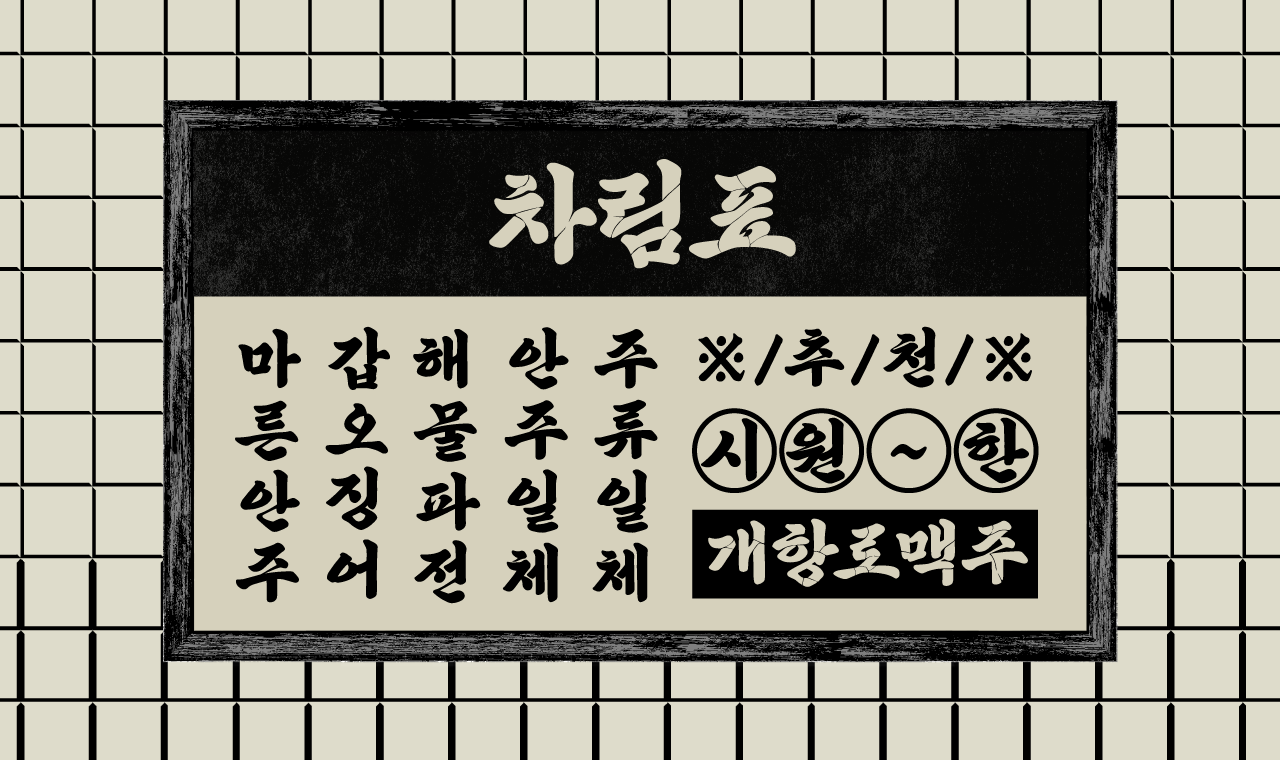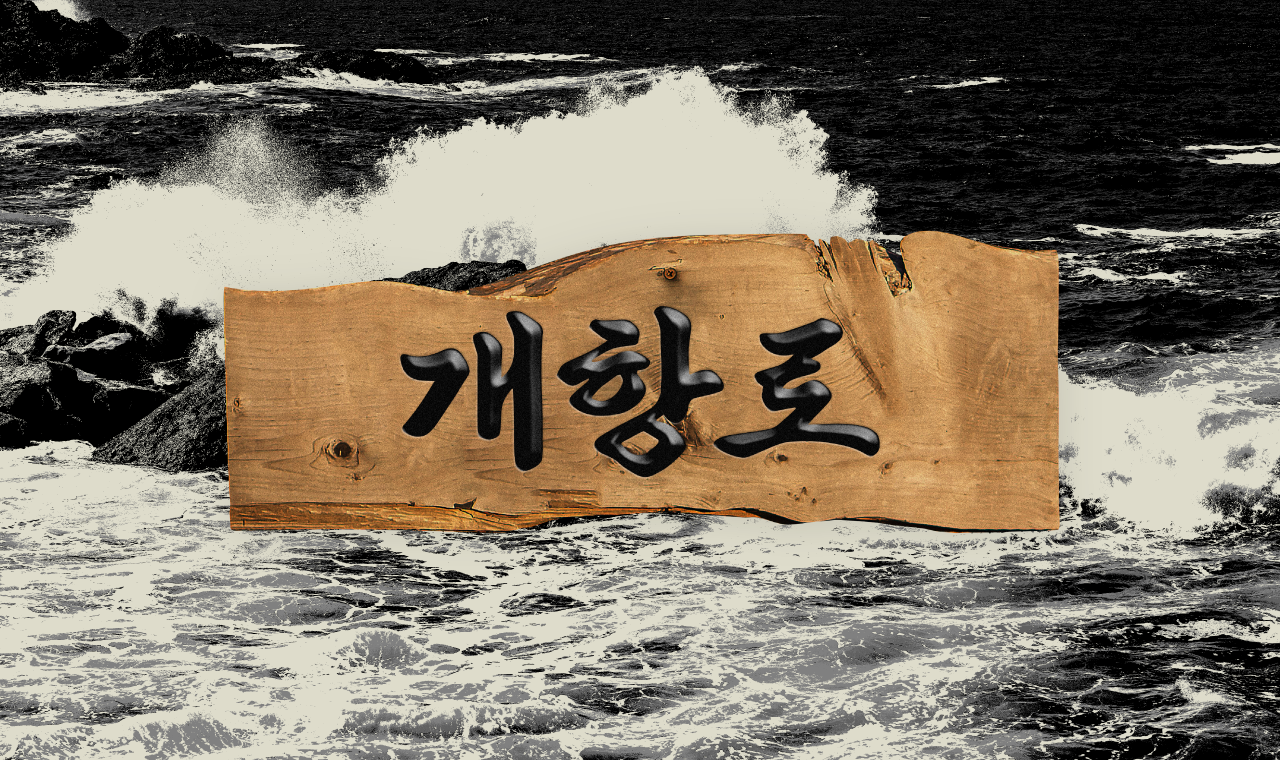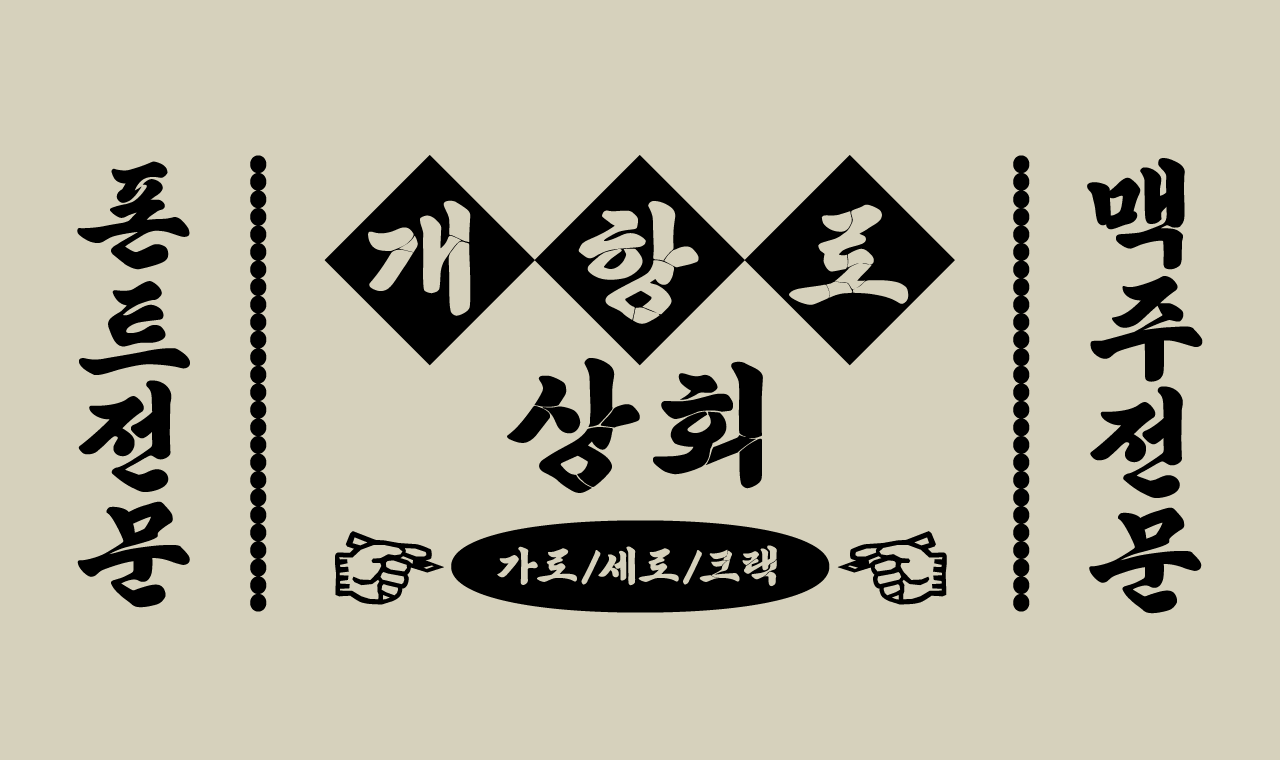
[]개항로 가로·세로·크랙
Yoon 개항로 가로·세로·크랙
개항로체는 윤디자인그룹과 로컬브랜딩의 우수사례인 인천 개항로 프로젝트의 협업으로 만들어진 서체입니다. ‘개항로 맥주’ 로고 타입을 제작한 전원공예사 전종원 작가의 목간판 글씨를 모본으로 개항로만의 지역성을 담아내어 개성 있는 글씨를 완성했습니다. 나무를 파고 색을 칠해 기존의 붓글씨 폰트와는 색다른 인상을 자아내는 목간판 글씨를 디지털 폰트 개항로체로 만나보세요.(2023. 8. 14. 개항로 가로) 여름에 출시한 ‘개항로 가로’에 이어 세로와 크랙 버전의 추가로 개항로 서체의 확장된 패밀리를 갖춥니다. 목간판에 쓰여진 만큼 세로쓰기에 적합하게 조정했으며, 크랙 버전은 개항로 서체의 원도가 되었던 개항로 맥주의 로고타입에서 시작되었습니다. 1883년 인천항 개항시기부터 140년의 세월이 느껴집니다.(2023. 12. 27. 세로, 크랙 버전 추가)